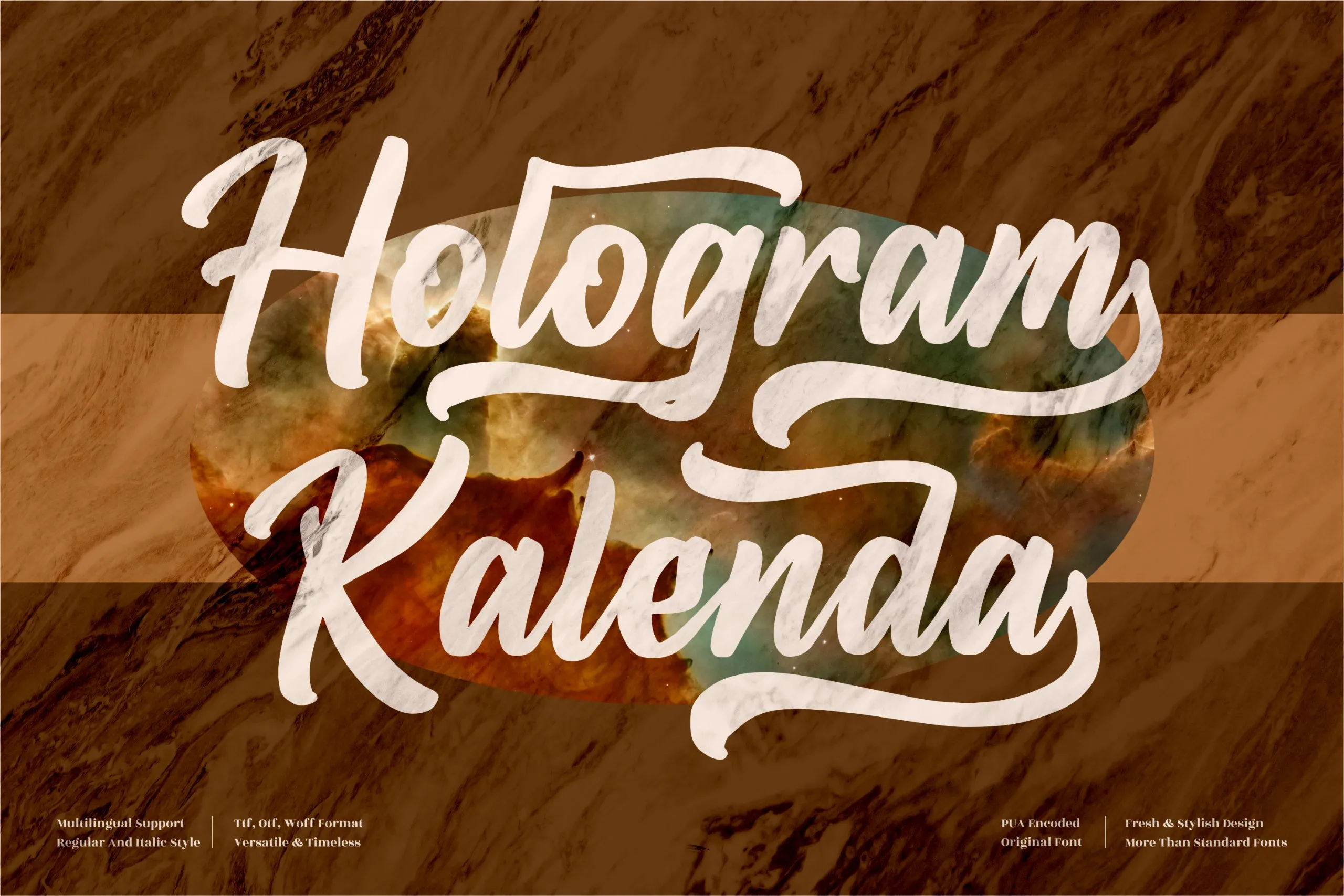
Hologram Kalenda Font – Fonte Grátis
Hologram Kalenda Font
A fonte ‘Hologram Kalenda Font’ é uma elegante escolha para quem busca adicionar um toque único aos seus projetos digitais. Se você está procurando por uma font que possa se adaptar a diversos tipos de trabalho, esta font é perfeita. Ela é ideal para criações como logotipos e projetos de marca, designs para móveis de casa e embalagens de produtos, tênis de moeda, cartões de lembrança, capas de livros, etiquetas, adesivos de papel, selos, design fotográfico, marcas ou até mesmo eventos especiais. Com sua beleza única e sofisticada, a ‘Hologram Kalenda Font’ é perfeita para qualquer projeto que deseja um toque diferenciado de alta qualidade. Sua elegância não só enriquece a visualização de seus trabalhos, mas também aumenta seu valor estético e funcional em qualquer aplicação.